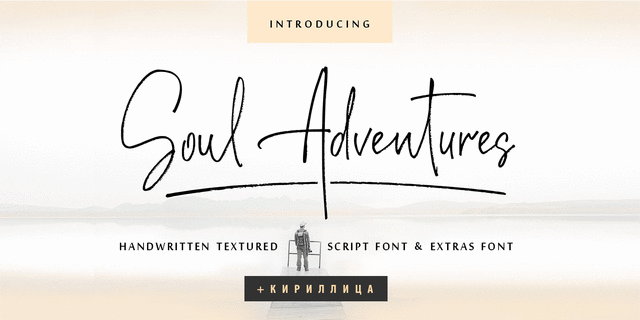
Шрифтовая пара Soul Adventures идеально подойдет для ваших свадебных приглашений, брендинга, логотипов, визиток, социальных сетей и упаковки. Soul Adventures Cyrillic включает полный набор заглавных и строчных букв, цифр, большой диапазон знаков препинания и 90 лигатур, придающих буквам реалистичный рукописный стиль.
Soul Adventures symbols – это шрифт, содержащий 36 нарисованных от руки элементов, иллюстрации и росчерки, которые помогут сделать ваш дизайн более оригинальным.
Многоязычная поддержка 32 языков + кириллица для русского, белорусского, украинского, болгарского и казахского языков. Шрифт разработала Ирина Двилюк в 2021 году.